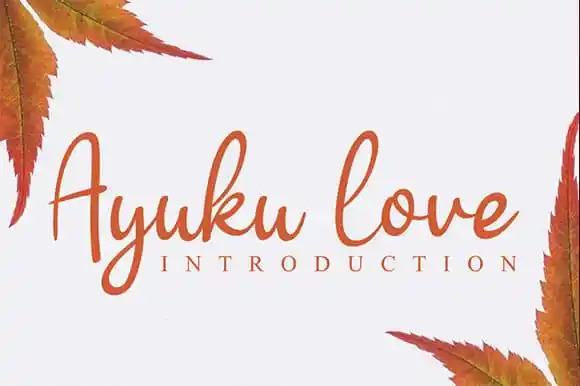
Ayuku love Script Font – Download Grátis
A Ayuku Love Script Font é uma deliciosa criação para projetos que precisam de uma pitada de elegância no texto. Este tipo especializado é perfeito para aprimorar qualquer projeto gráfico, seja ele para publicações nas redes sociais ou como logotipos de produtos, embalagens ou até mesmo capas de livros e revistas. Com sua forma fluida e delicada, essa fonte traz um toque suave ao seu design, tornando-a perfeita para ambientes em que a elegância e a simplicidade se misturam. Seja você designer gráfico ou criador de conteúdo digital, a Ayuku Love Script Font está aqui para transformar seu projeto com um charme único. Ideal tanto para aplicativos em tela grande como para uso na web, essa fonte irá deixar seu trabalho ainda mais especial e memorável. É uma escolha perfeita para qualquer projeto que valoriza uma pitada de graça na escrita manual.